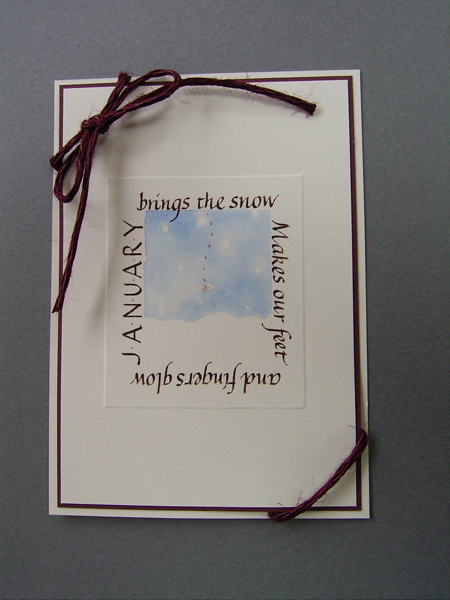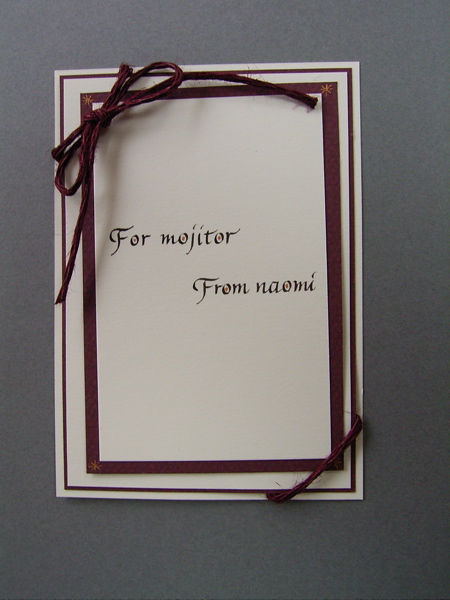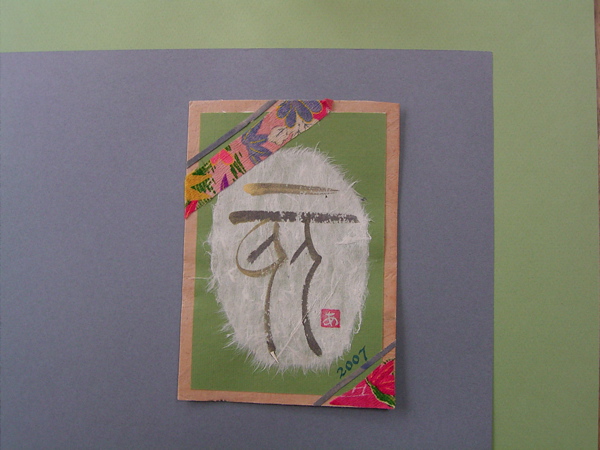
1月のエクスチェンジカード
1月のエクスチェンジカードです。
こちらはakaneさんのカードです。とても和風。
そうです、1月のカードだから年賀状の感じですよね。この筆で書いてある文字はなんと読むのでしょう。亥かな??(すみません、漢字がよくわからなくて・・・)
私が素敵!と思ったのはこのななめに貼ってある布のきれはしです。本物の絹の織物の様ですよ。むかしの古裂みたいです。着物や小物と違った場面で活躍です。地の色がピンクで可愛いですね。
何に使われていたものでしょうね。子供の晴れ着の下に着る長襦袢の裏地とか?
やはり日本人です。和風は本当にほっとしますね。
こちらは茶色と水色という大人っぽい色の組み合わせ。テーマは雪です。
雪の静けさと冷たさ、心の中のほんわかする暖かさが伝わります。愛情を持った目で雪を見ている気持ちがよくわかりますね。
ヒラヒラと舞い降りて来て、足下と指先を照らしてくれるのですね・・・・・
う〜ん、素敵!カードの中に小さな世界がありますねー!
筆文字は、そうです、「亥」の篆書(てんしょ)古代の文字です。